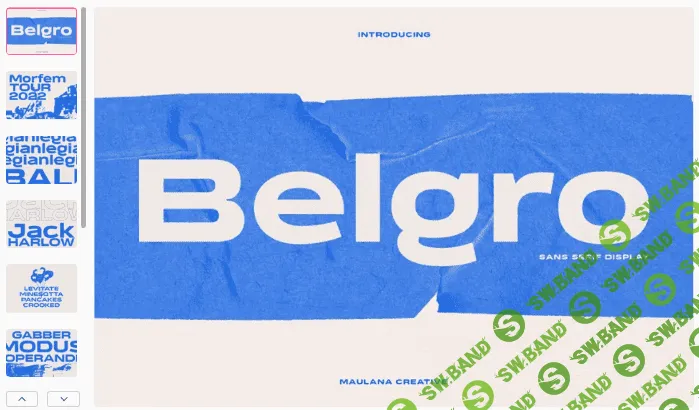
Название: Belgro Font (2022)
Belgro — современный шрифт без засечек. С жирным штрихом, веселым характером с небольшим количеством лигатур и чередований. Чтобы дать вам дополнительную творческую работу. Шрифт Belgro поддерживает многоязычность более чем на 100+ языках. Этот шрифт хорош для дизайна логотипа, социальных сетей, названий фильмов, названий книг, короткого текста, даже длинного текстового письма, а также подходит для шрифта вторичного текста с без засечек или без засечек. Сделайте потрясающую работу со шрифтом Belgro.